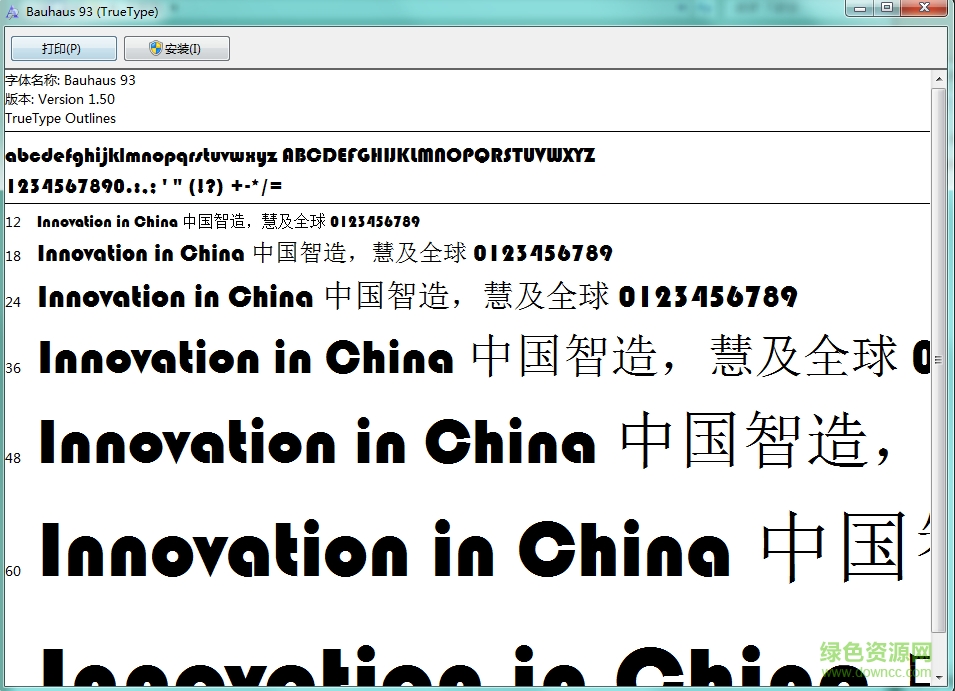
Bauhaus 93是一款非常適合制作果凍狀文字的藝術(shù)字體,讓英文字體有著優(yōu)美圓滑的弧度,中文字體簡(jiǎn)潔干練,喜歡的朋友歡迎來(lái)綠色資源網(wǎng)免費(fèi)下載哦!
Bauhaus 93是一款很適合photoshop編輯和各類(lèi)平面設(shè)計(jì)、logo品牌制作的ps字體,對(duì)英文字體有著獨(dú)特而美觀(guān)的修飾性,很多網(wǎng)友制作的果凍字體都有它的功勞哦!